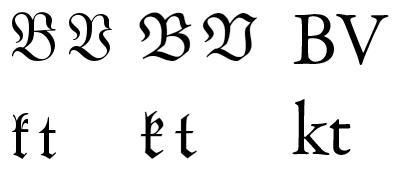
Neue Rechtschreibung?
Die Gestaltung des Dokumentes hat mit dem Ergebnis insofern zu tun, als daß ich daraus ablesen kann, wieviel Mühe darauf verwendet wurde und welche Erfahrung ihr Urheber mit der Materie hat. Rechtschreibung und Typografie dienen der Lesbarkeit, und mir scheint, der Student hat sich darum nicht geschert. Aber auch sonst niemand. Haben die Betreuer die Arbeit gelesen? Sieht nicht so aus. Sieht eher nach Durchwinken aus.
An mir sind in den letzten Jahrzehnten etliche Versuche vorbeigerauscht, die Lesbarkeit berechenbar machen wollen. Keiner war überzeugend genug, um mir im Gedächtnis zu bleiben. Also nein: ich erinnere mich an keinen. Ich bin sogar so frech zu behaupten: Es gibt keine. Das ist keine Wissenschaft. Du wolltest mir das Gegenteil mit einer Bachelor-Arbeit beweisen, die in der Einleitung darauf hinweist, daß ihre Ergebnisse nicht verallgemeinerbar sind, die also gar keine Aussagekraft außer einer möglichen (ebenso gut nicht möglichen) Tendenz hat. Hast du noch was Handfestes?
Der Sehtest ist nötig, um die Probanden gleicher zu machen. Man erkennt mit einer bestimmten Unschärfe womöglich andere Dinge als mit einer anderen bestimmten Unschärfe. Das weiß ich nicht. Das müßte ein Augenarzt sagen können. Wozu ist denn die Sehstärke in dem Text angegeben? Und Alter und Geschlecht? Um eine Normalverteilung zu simulieren? Die wird aber gar nicht erwähnt. Wie ist denn die Normalverteilung? Und wo? Provinzbevölkerung? Großstadtbevölkerung? Welches Millieu?
Ein Lektor liest anders als ein Klempner.
Spielt auf der Autobahn keine Rolle. Und ansonsten möchtest Du wohl Apotheker zum Maßstab nehmen, da diese absolut alles (ausgehend von Arztschriften) lesen können?
Und der Rant gegen die BA-Arbeit empfinde ich als unnötig. Ohne zu wissen, welchen Abschnitt das PDF im Abgabe-Prozess abbildet, ist die Aussage "legasthenische Darbietung" mehr als unhöflich und ziemlich verletzend für alle, die an dieser Behinderung leiden.
Sieht eher nach Durchwinken aus.
Du wolltest mir das Gegenteil mit einer Bachelor-Arbeit beweisen, die in der Einleitung darauf hinweist, daß ihre Ergebnisse nicht verallgemeinerbar sind
Das war nur ein Beispiel, als Antwort auf deine Infragestellung von Theorie/Lösung/Überprüfung meiner Aussagen. Hier wurde eine Schrift mit einem ganz konkreten wissenschaftliche Methoden entwickelt und anschließend von unabhängiger Seite überprüft. Das zeigt, dass diese Verknüpfung von Schriftdesign und Wissenschaft scheinbar möglich ist. Ich kenne ansonsten auch niemand, der das anzweifeln würde. Es tut sich erfreulicherweise auch gerade sehr viel in diesem Bereich. Also ausdrücklich in Kooperation von Designer und Wissenschaftlern. So kann jede Seite die Fehler des anderen ausmerzen.
Wenn in deiner Arbeit wissenschaftliche Leserlichkeitaspekte keine Rolle spielen, ist das auch in Ordnung. Ich würde mir aber etwas mehr Respekt vor der Arbeit anderen wünschen, die diesen Weg gehen. Wenn eine Studie nicht nach ihrem Versuchsaufbau, sondern nach dem Ort der Entstehung oder der Gestaltung ihrer Dokumentation beurteilt wird, dann ist das äußerst unsachlich. Wir sind hier schließlich nicht am Stammtisch, sondern du spricht hier öffentlich. Der Beitrag hat dauerhaften Bestand und wird gegebenenfalls auch von den beteiligten der Studie gelesen.
Hast du noch was Handfestes?
Sicher. Aber gemessen am Stil deiner letzten Beiträge, kann ich kein ernsthaftes Interesse an einer inhaltlichen Auseindersetzung mit diesem Thema erkennen. Insofern werde ich davon absehen, weitere Belege vorzulegen.
Der Sehtest ist nötig, um die Probanden gleicher zu machen.
Und warum sollte man das tun? Sollen die auch alle gleich alt, gleich gebildet, gleich belesen usw. sein? Diese Gleichheit gibt es nicht, und wenn man sie hätte, würde das Ergebnis ja wieder nur für diese kleine Gruppe, nicht für den Durchschnitt gelten.
Denn letzteres ist das interessante Ergebnis. Man kann für alle erfassten Daten natürlich auch die Ergebnisse einzeln ausrechnen. Also gibt es für Männer/Frauen, ältere, weitsichtige/kurzsichtige, Stadtbewohner/Landbewohner, gebildete/ungebildete, Linkshänder/Rechtshänder usw. signifikante Abweichen vom Durchschnitt. Teilweise wurde das auch gemacht. Das ist auch alles möglich und interessant, aber es macht die Frage nach dem Durchschnittsergebnis aller Teilnehmer nicht obsolet. Ganz im Gegenteil.
Du weißt schon, daß sich unsere heutige Schriftsprache zu einer Zeit entwickelte, als man für das Deutsche nur gebrochene Schriften benutzte? Unsere Schriftsprache hat sich deshalb sehr wohl zusammen mit der gebrochenen Schrift entwickelt. Und selbstverständlich haben sich Schrift und Schriftsprache dabei gegenseitig beeinflußt (siehe zum Beispiel das Eszett).